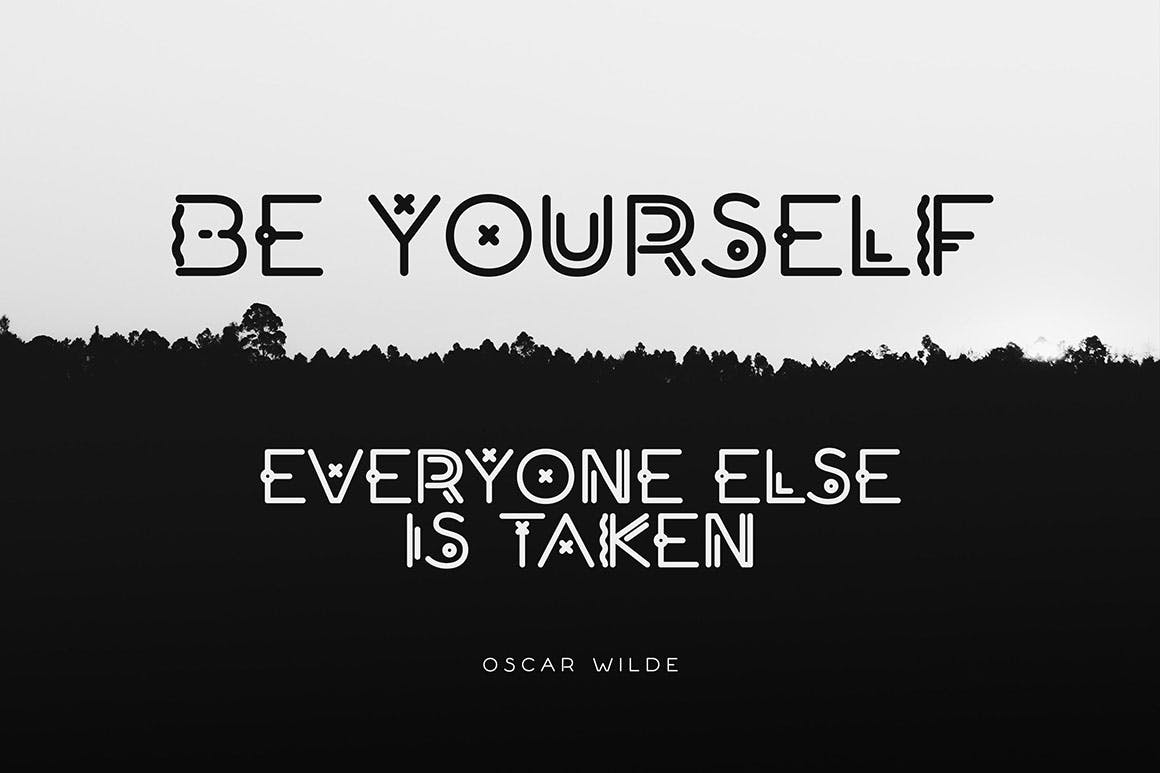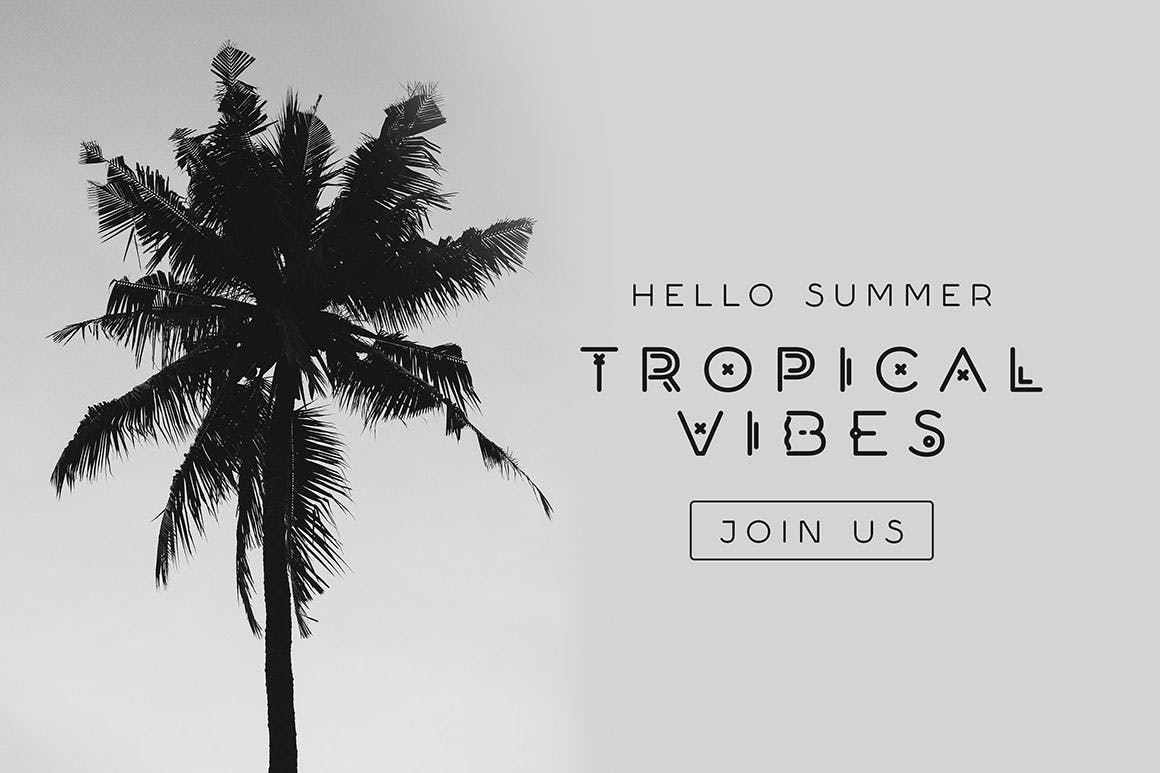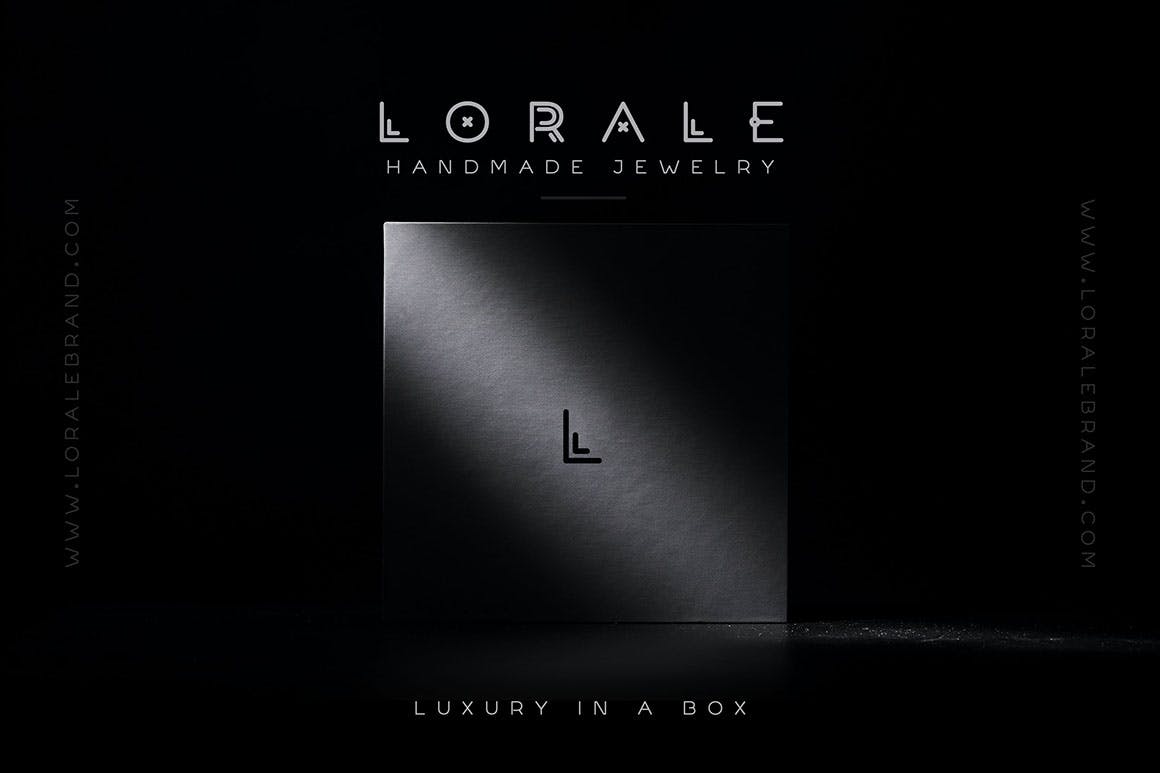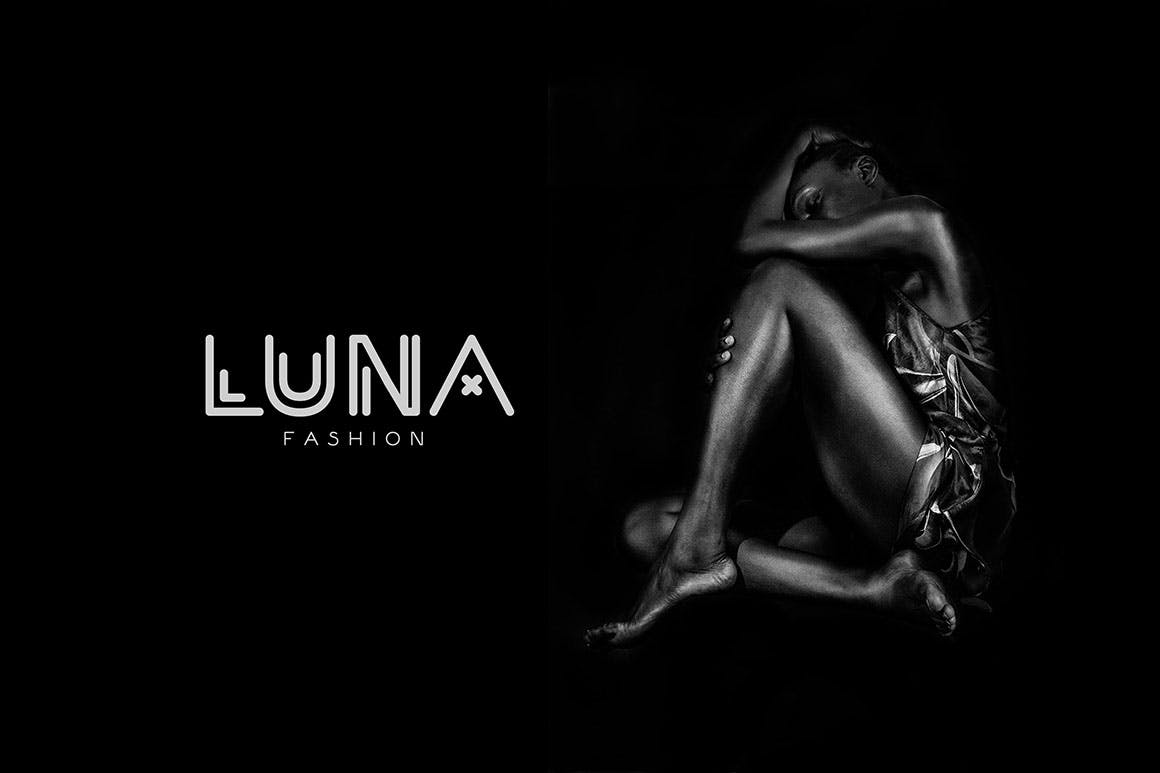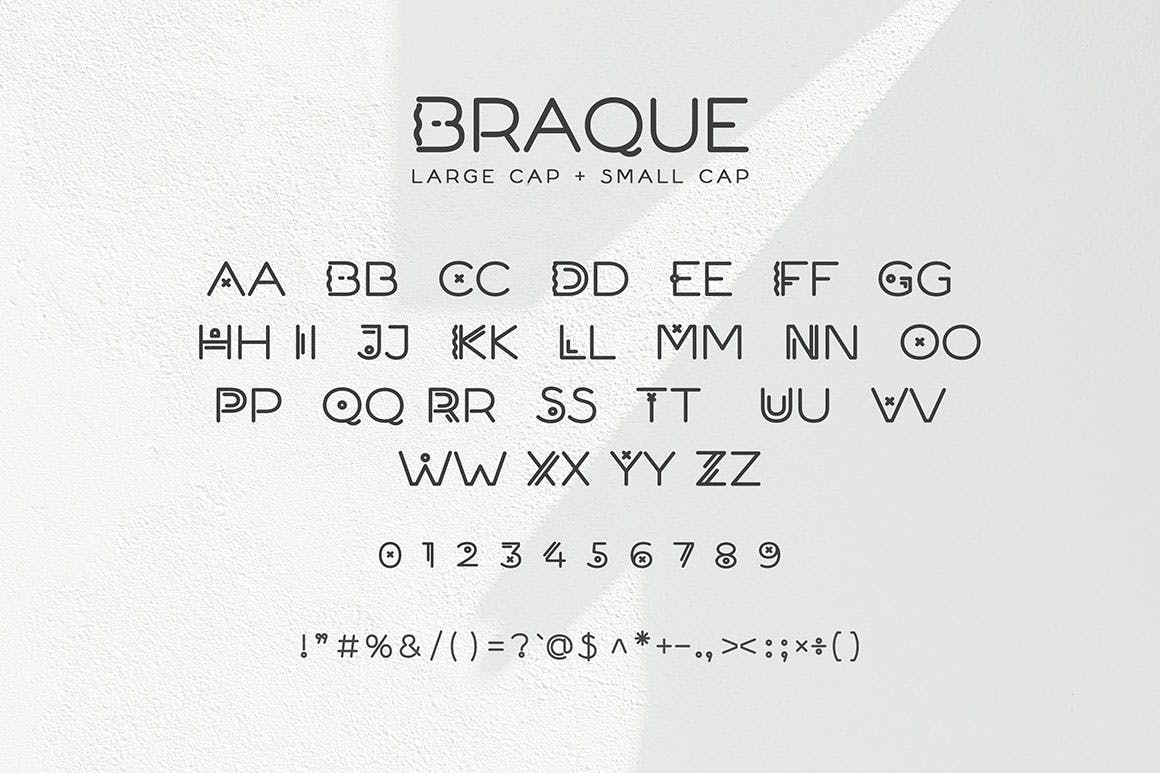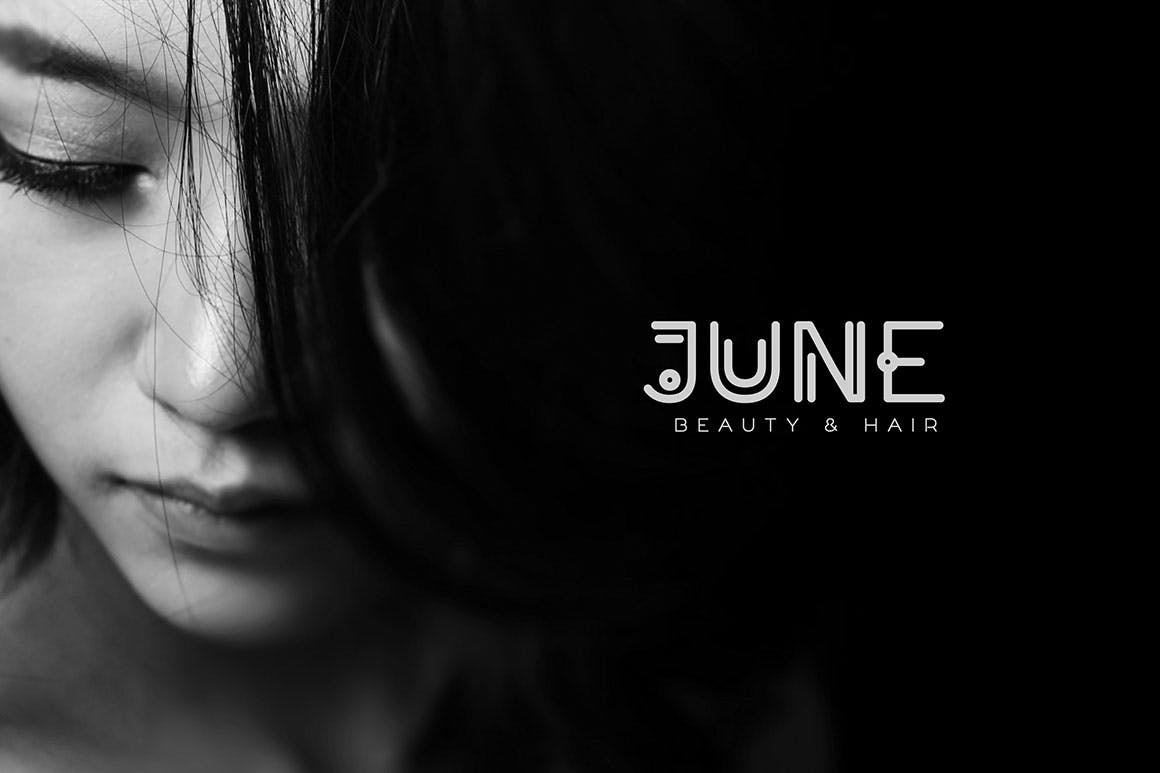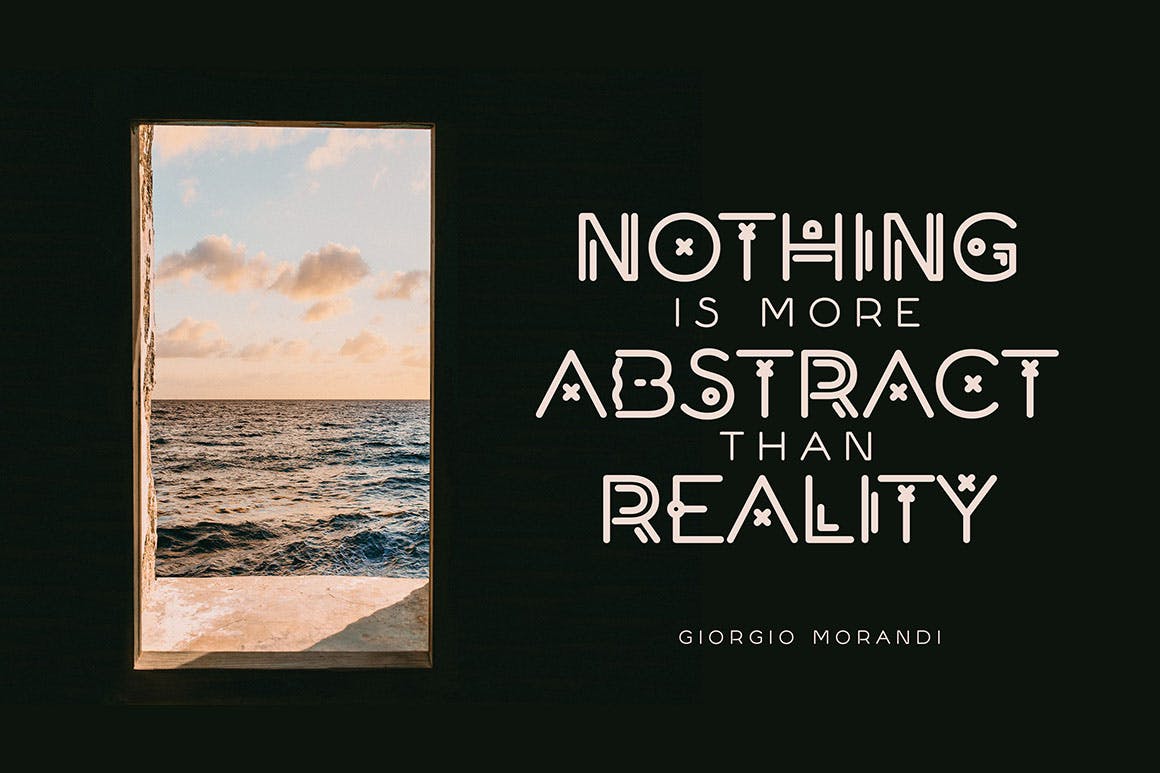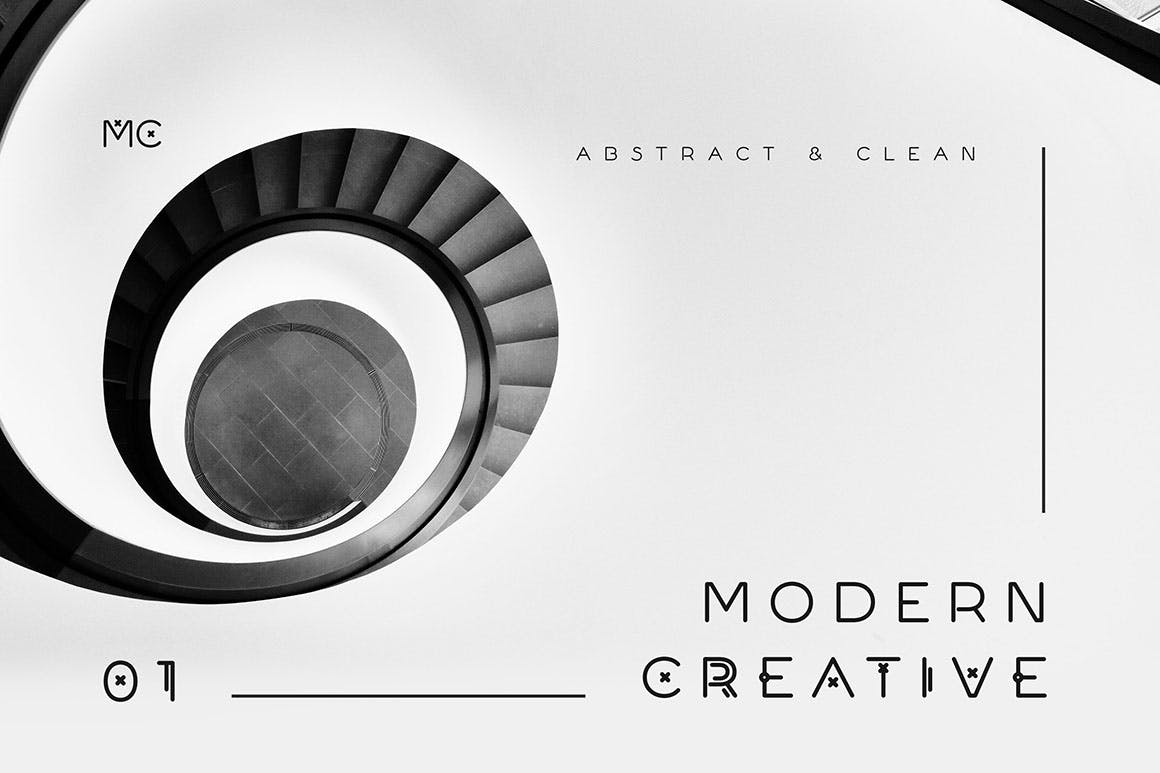
معرفی فونت Braque - یک فونت لوگو مدرن و هندسی با حس مینیمالیستی.
این فونت انتزاعی برای استفاده در تیترها، عناوین، لوگوها، پوسترها، بروشورها و هر چیزی که به یک نوعچهره هندسی و مدرن نیاز دارد، طراحی شده است.
فونت شامل مجموعهای از حروف لاتین در حروف بزرگ و کوچک به همراه نمادهای ویژه است.